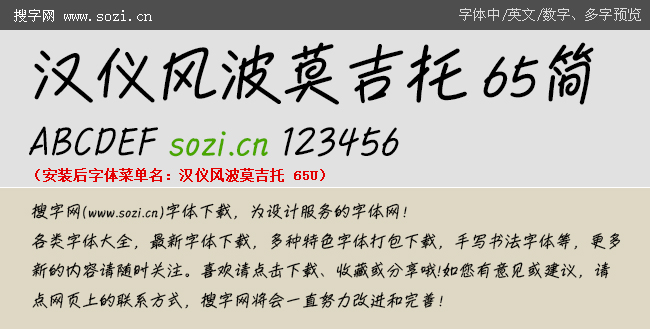
漢儀風(fēng)波莫吉托 65簡(jiǎn)
搜字網(wǎng)給大家提供一款漢儀風(fēng)波莫吉托 65簡(jiǎn)中文字體下載,漢儀風(fēng)波莫吉托是一款具有獨(dú)特藝術(shù)風(fēng)格的字體,筆畫(huà)流暢自然,富有動(dòng)感和節(jié)奏感。線條的粗細(xì)變化豐富,能展現(xiàn)出獨(dú)特的韻律。整體風(fēng)格較為優(yōu)雅,具有一定的文藝氣息,同時(shí)又不失現(xiàn)代感。適用于畫(huà)冊(cè)設(shè)計(jì)、海報(bào)設(shè)計(jì)、包裝設(shè)計(jì)等場(chǎng)合使用。(本字體為個(gè)人非商用版,如需要商用請(qǐng)聯(lián)系漢儀公司購(gòu)買(mǎi)版權(quán))